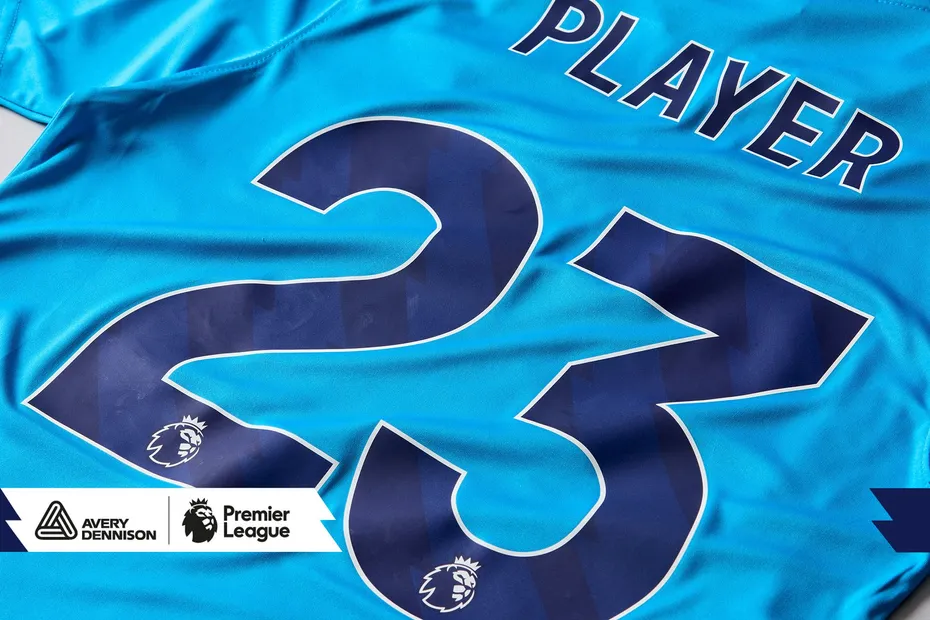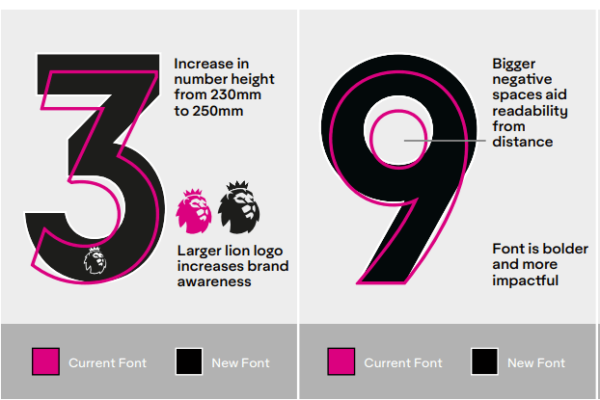
Premier League, presentato un nuovo font: più leggibile a distanza
La Premier League sta per introdurre un nuovo tipo di carattere per le maglie delle squadre a partire dalla stagione 2023-2024. Il font è stato creato in collaborazione con Avery Dennison, che ha sostituito Sporting ID come fornitore ufficiale della Premier League nel 2019.
Secondo la Premier League, il nuovo tipo di carattere è stato progettato per migliorare l’esperienza dei tifosi, rendendo più facile per loro identificare i giocatori e seguire la partita. Il font sarà utilizzato per i nomi dei giocatori e i numeri sulle maglie, nonché per i distintivi delle maniche delle maglie.
Il nuovo tipo di carattere sarà disponibile in una vasta gamma di colori, che consentirà alle squadre di personalizzare le loro maglie in base ai propri colori sociali. Ciò garantirà che ogni squadra abbia un look unico e riconoscibile.
Il nuovo tipo di carattere è stato testato in campo dai commentatori della Premier League Martin Tyler, Jim Proudfoot e Joe Speight, presso lo stadio della squadra del Brentford, il Gtech Community Stadium. Secondo i commentatori, il nuovo font è molto leggibile e facile da identificare, il che lo rende ideale per i tifosi che seguono la partita da casa.
Il nuovo tipo di carattere è stato creato per sostituire il font attuale, che è stato introdotto nel 2017. Il font attuale ha ricevuto alcune critiche da parte dei tifosi, che lo hanno trovato difficile da leggere e poco attraente. Il nuovo tipo di carattere è stato progettato per risolvere questi problemi e migliorare l’esperienza generale dei tifosi.
Il Chief Commercial Officer della Premier League, Will Brass, ha dichiarato: “Il tipo di carattere è diventato parte integrante dell’identità della Premier League. Siamo felici di poter lavorare con Avery Dennison per creare un nuovo tipo di carattere che sia moderno e leggibile, ma che mantenga anche l’identità della competizione.”
Il nuovo tipo di carattere della Premier League è un esempio di come la tecnologia possa essere utilizzata per migliorare l’esperienza dei tifosi. Offrendo un design moderno e leggibile, la Premier League sta dimostrando il proprio impegno per l’innovazione e l’eccellenza.
Sarà interessante vedere come i tifosi reagiranno al nuovo tipo di carattere quando le nuove maglie verranno presentate in vista della stagione 2023-2024. Tuttavia, la Premier League è fiduciosa che il nuovo tipo di carattere riceverà un’accoglienza positiva da parte dei tifosi e delle squadre.